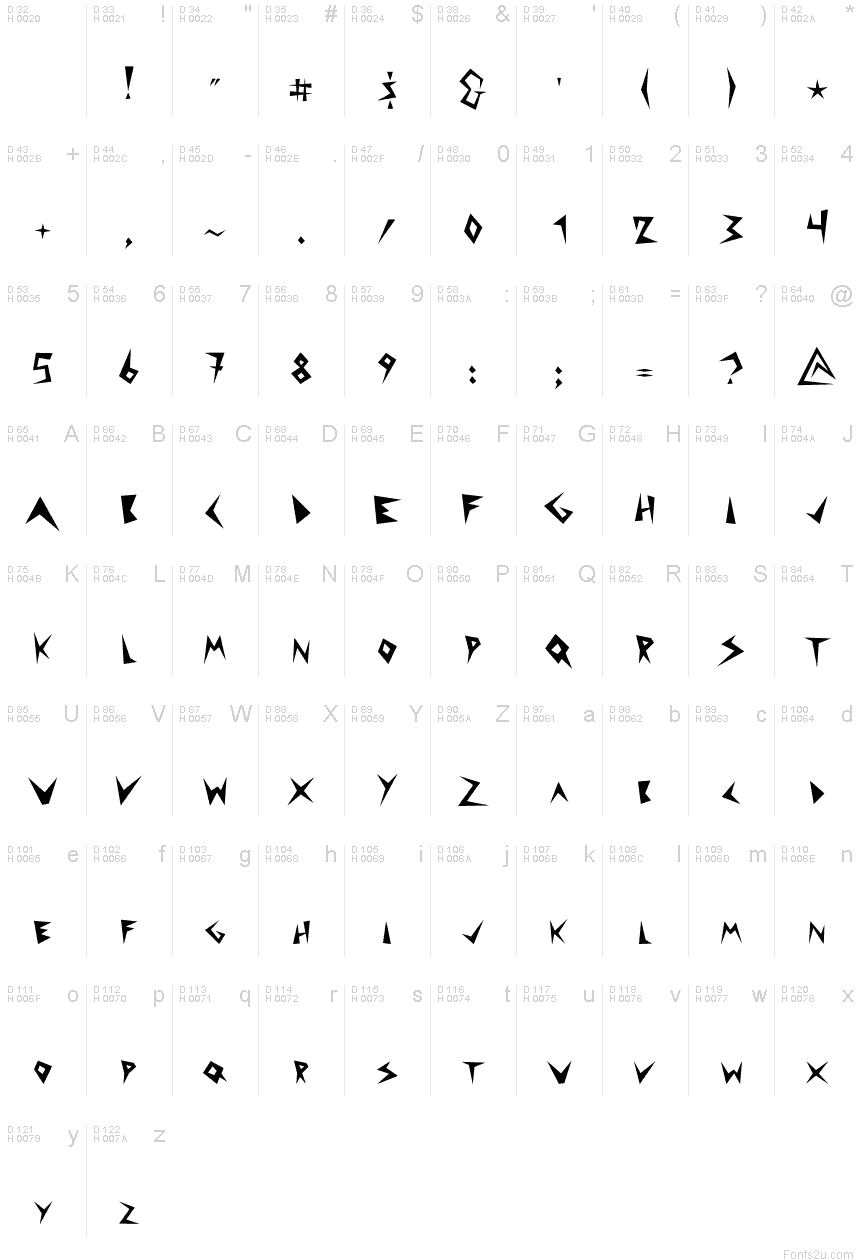
puntúa display
PUNTA DISPLAY.
La tipografa para enterrar en todas partes, matar y dejar ciegos a lectores odiados. made in Chile, realizada como proyecto personal para un afiche.